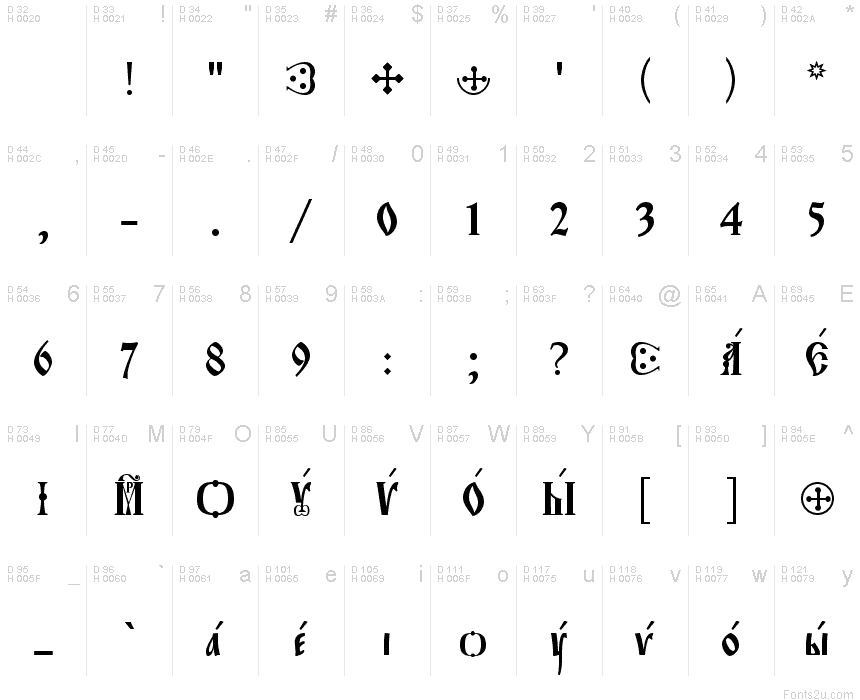
“Orthodox tt eRoos SpacedOut”, di SoftUnion Ltd e N. Andrushchenko, è un font display cirillico gratuito dal tono decisamente ecclesiastico. Le lettere appaiono cerimoniali ed essenziali, costruite con forme alte e arrotondate dal forte contrasto, e caratterizzate da punti simili a perline sopra e sotto che conferiscono al font un ritmo rituale, quasi come un'icona.
È una scelta naturale per bollettini parrocchiali, locandine di festival folk, copertine di libri, cartelli di titoli e brevi grafiche museali dove serve un'atmosfera slava o liturgica senza troppi fronzoli. Funziona al meglio in contesti brevi – iniziali, titoli di copertina e intestazioni compatte – perché è il motivo ripetuto dei punti a fare gran parte del lavoro.
Orthodox eRoos is a font which implements the Extended ROOS encoding that is containing Church Slavonic characters allocated according to the ROOS standard, Arabic numerals and special symbols (Typikon symbols, Mark's chapter symbols, etc). This font created on the basis of the font Evangelie by N. Andrushchenko